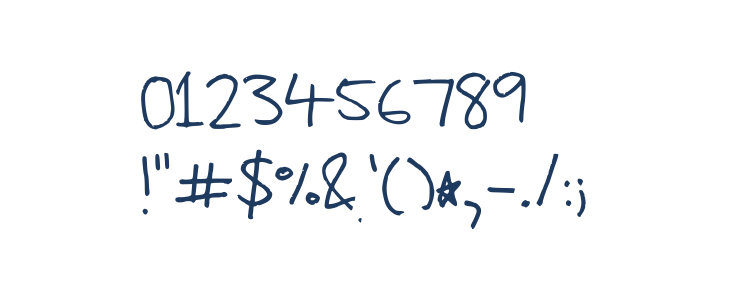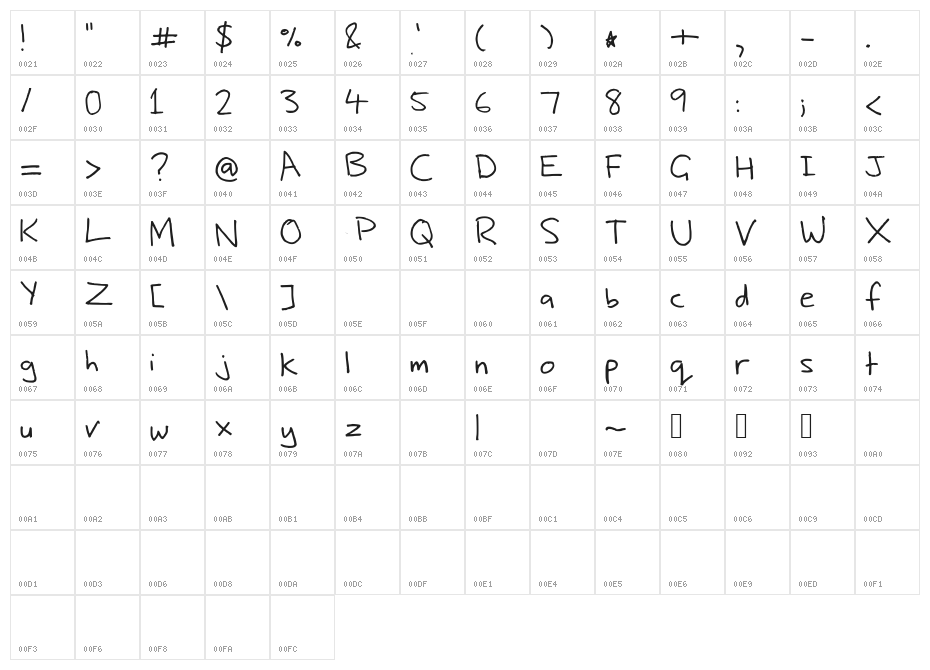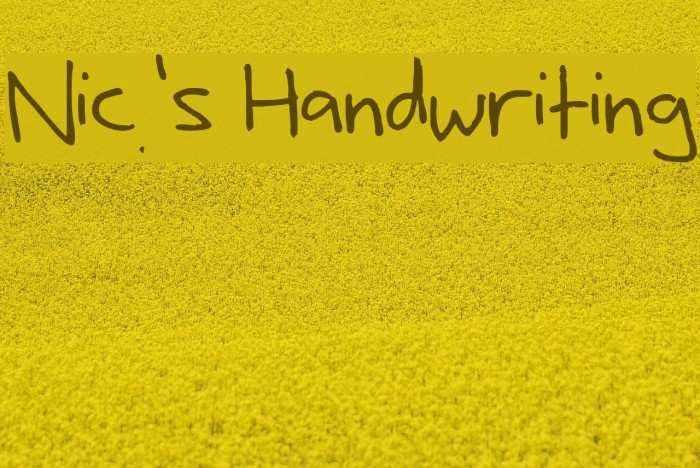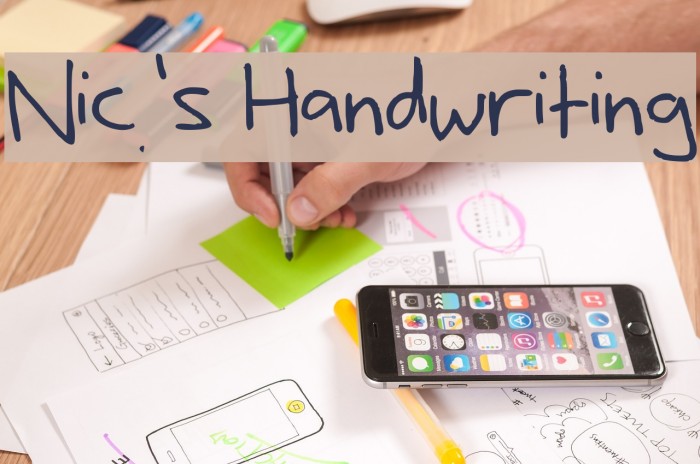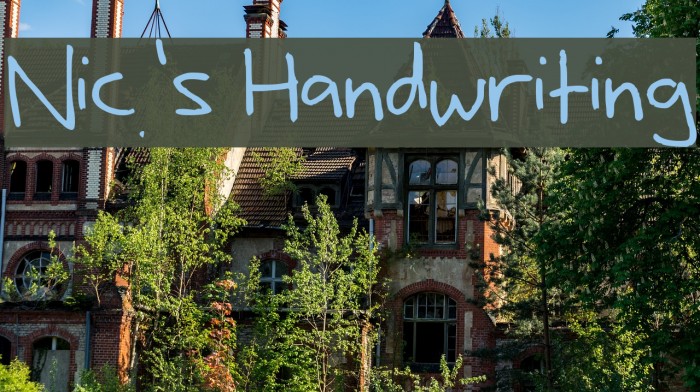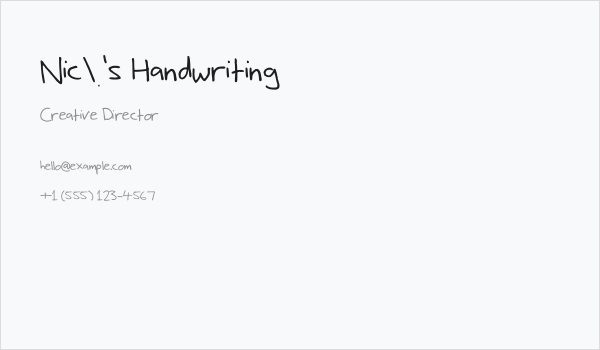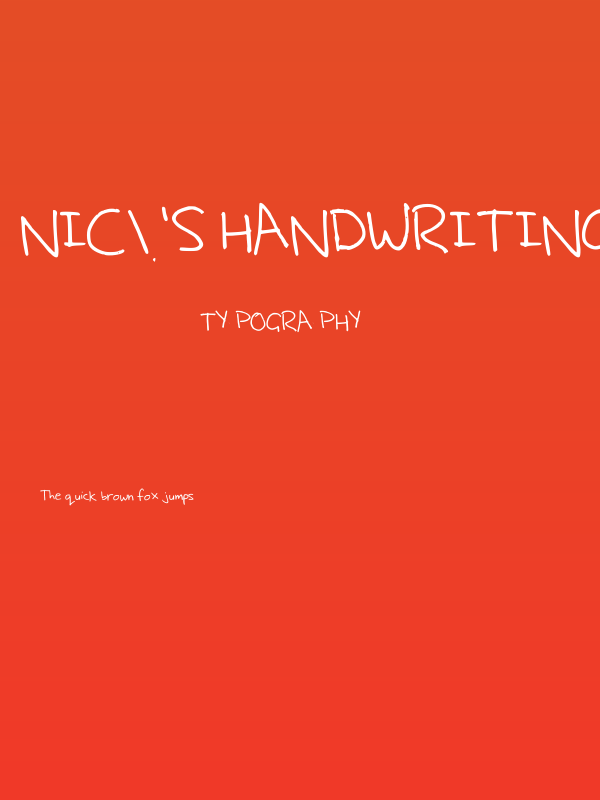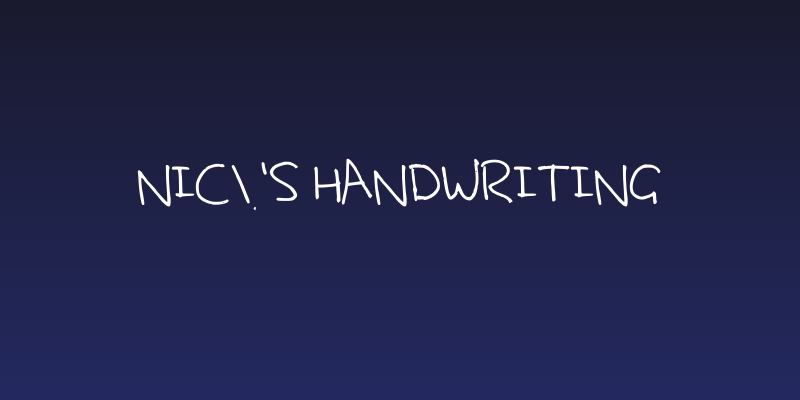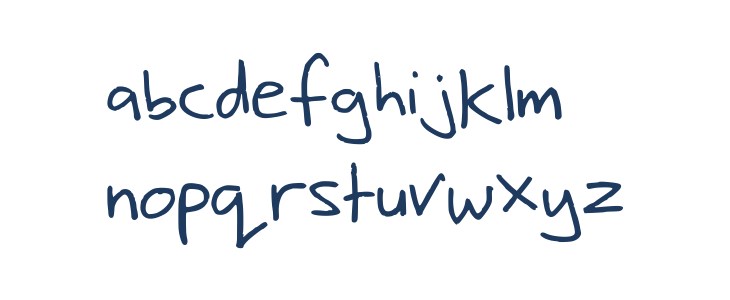
Nic's Handwriting Font
| Stile generale | Casual, Playful |
| Caso d'uso | Headlines, Informal text, Creative projects |
| Progetti proposti | Ideal for greeting cards, personal notes, creative projects, and informal branding. |